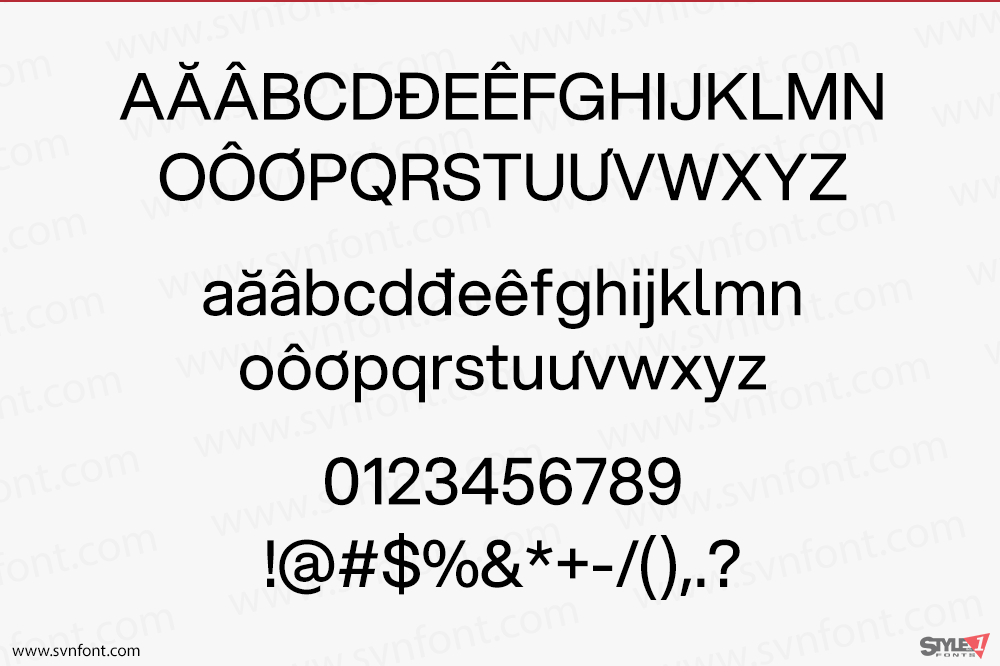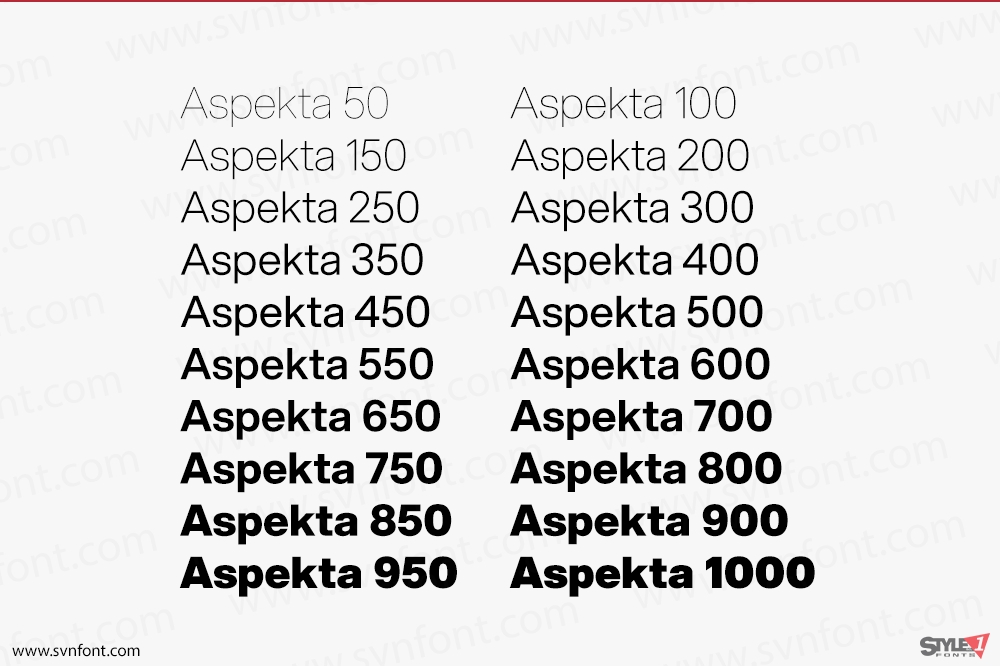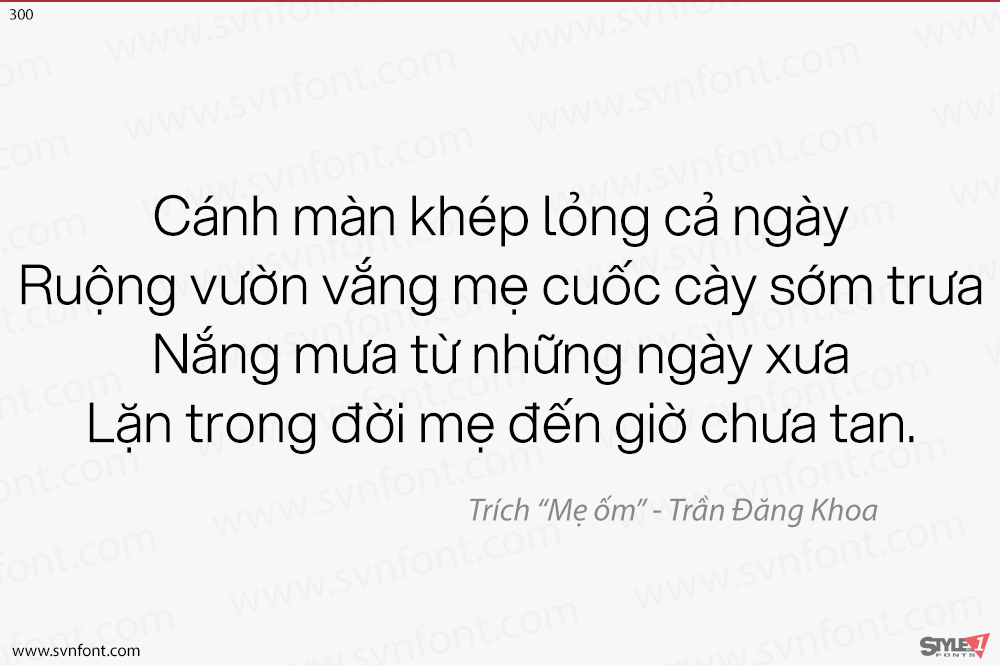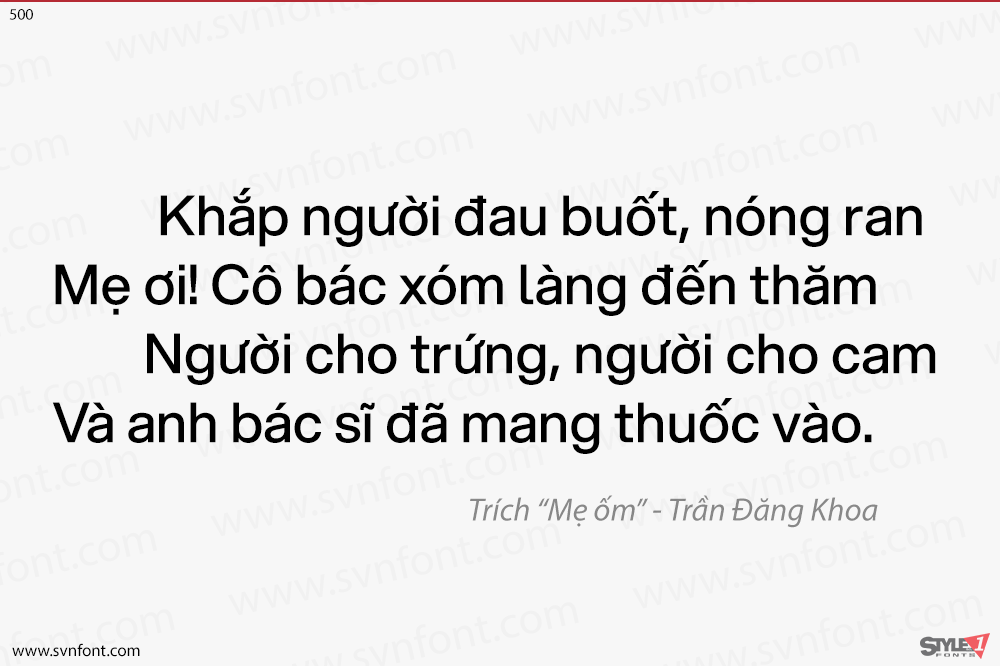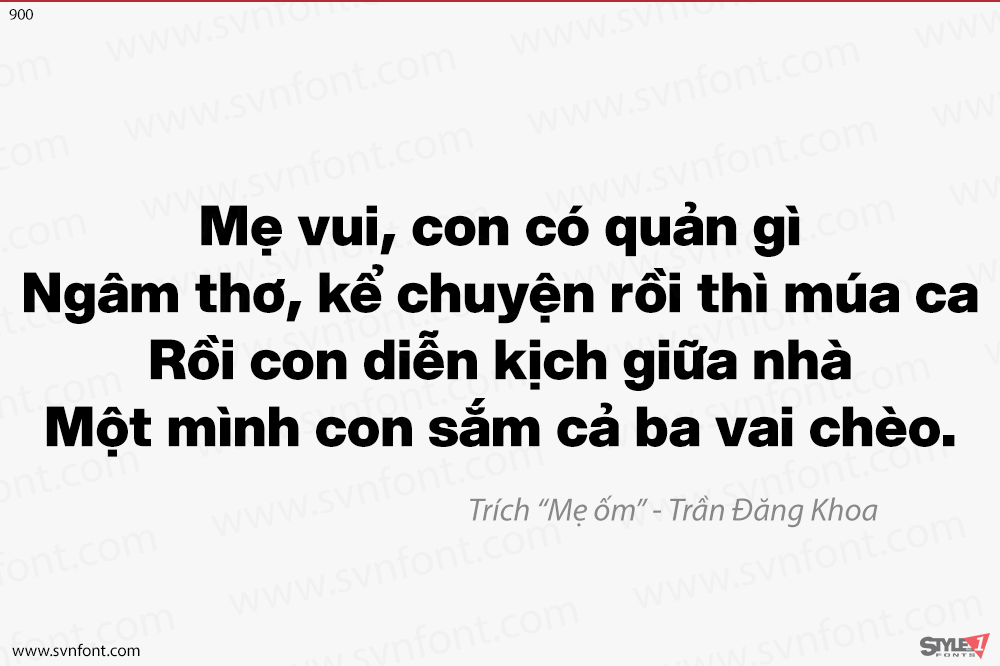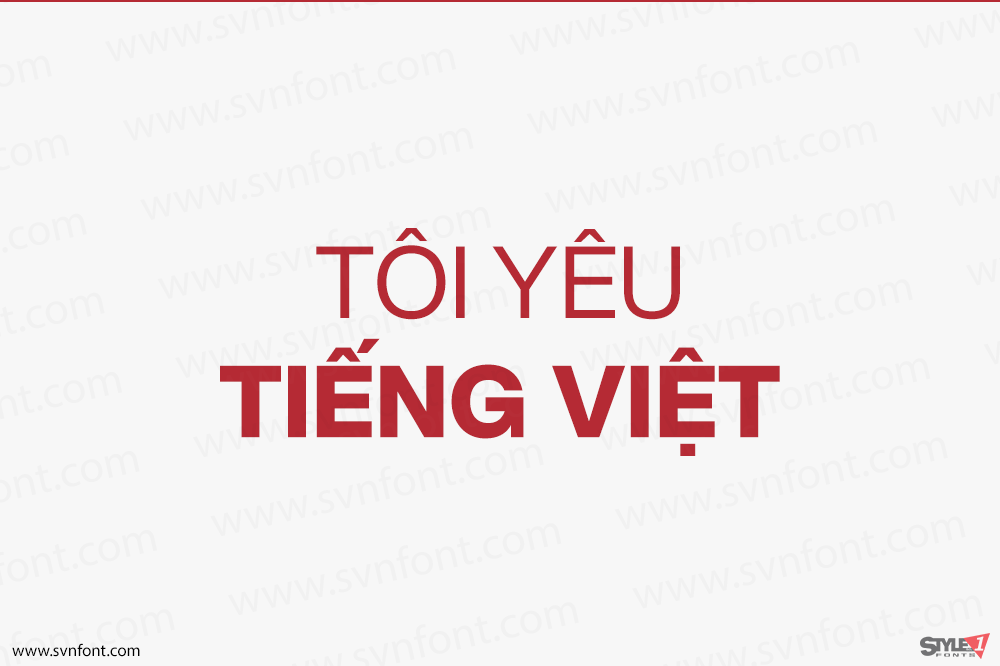
[Việt hóa] SVN-Aspekta (20 fonts) + Variable
A modern sans-serif collection inspired by a clean, simple and neutral style. The family provides a wide range of weights and stylistic alternatives that can be mixed to create strong branding.
Nhà thiết kế: Ivo Dolenc